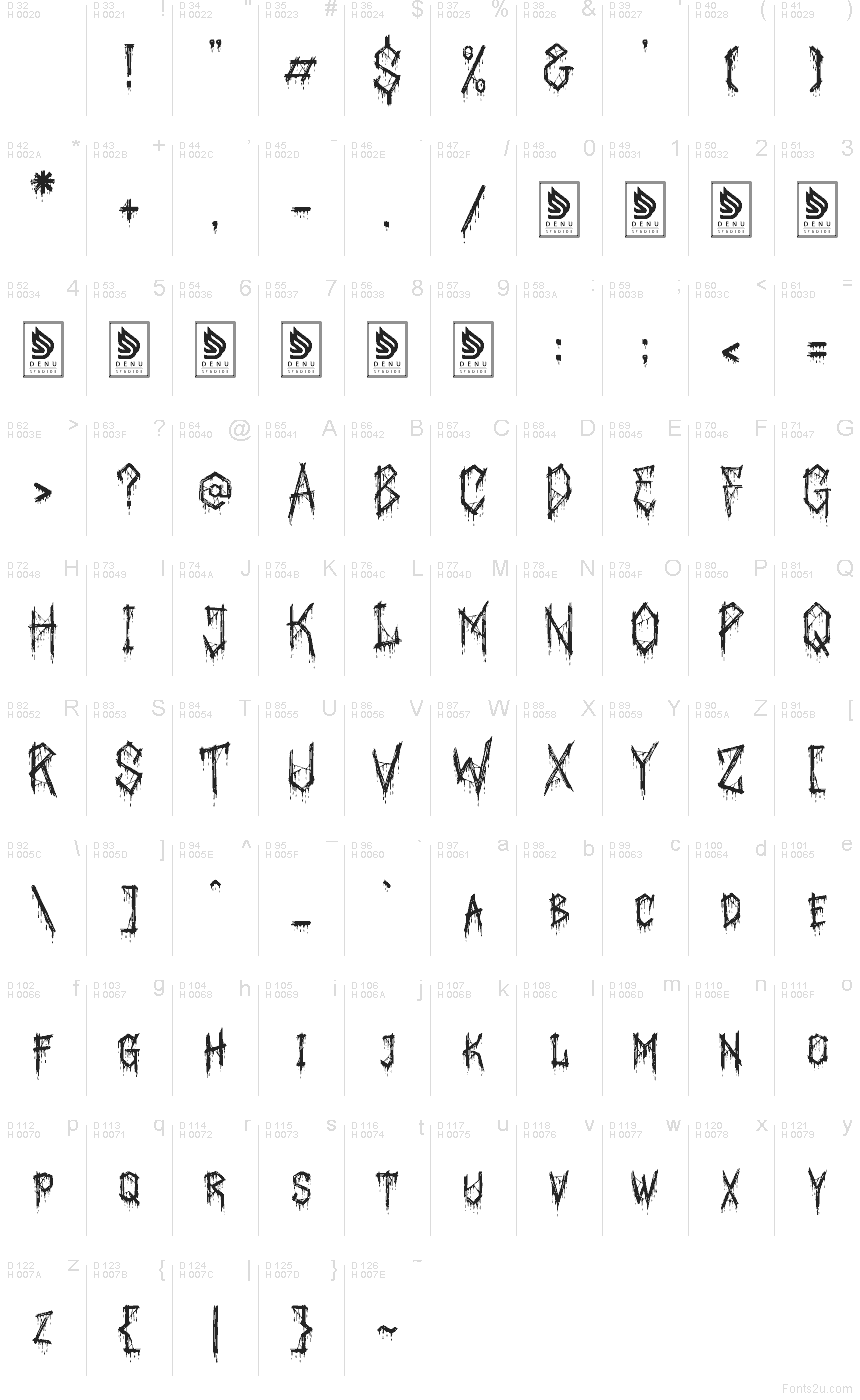
Eternal Torment di Denustudios è un font horror gratuito che evoca l'aspetto di bastoni scheggiati legati insieme, da cui sembra colare qualcosa di sinistro. Le maiuscole trasmettono un senso crudo e frenetico, con angoli irregolari, barre trasversali non allineate e finali striati che lo spingono verso i titoli da film slasher e la segnaletica occulta fatta a mano, piuttosto che verso una tipografia gotica ordinata.
Utilizza questo font gratuito per titoli di poster, copertine di album, schermate di caricamento di giochi, volantini per attrazioni horror e fanzine dove le lettere devono sembrare graffiate nell'oscurità. È perfetto anche per brevi testi di copertina, incipit di capitoli e titoli, poiché i suoi tratti ruvidi e pendenti conferiscono a qualsiasi parola una tensione instabile.